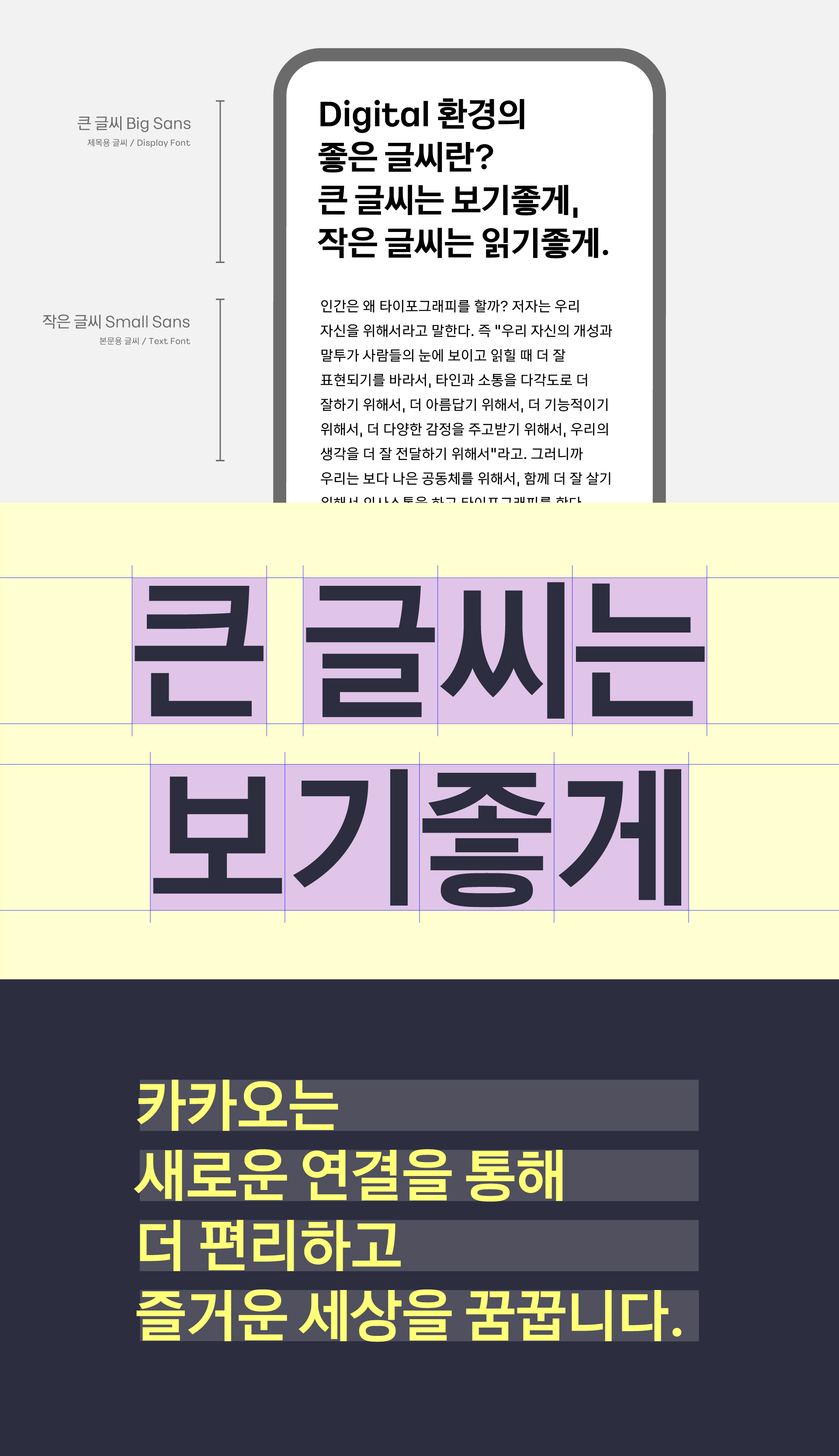
소개
정보 전달과 감정 표현을 모두 세심히 고려하여, 디지털 시대의 새로운 문화를 반영한 글꼴입니다. 각각 작은글씨와 큰 글씨로 분류되며, 디지털 기기에 맞춰 가독성이 좋게 만들어진 폰트 입니다. 폰트의 표현방식에 따라 큰 글씨와 작은 글씨를 맞춰서 사용하시면 효과를 극대화 하실 수 있습니다.
- 카카오 큰글씨는 단단하고 안정적인 조형을 갖춘 서체로, 제목과 본문에서 명확한 정보 전달에 적합하도록 설계되었습니다.
- 카카오 작은글씨는 넉넉한 글자 간격과 확장된 속공간을 적용하여, 작은 디스플레이에서도 뛰어난 가독성을 제공합니다.
서체구성